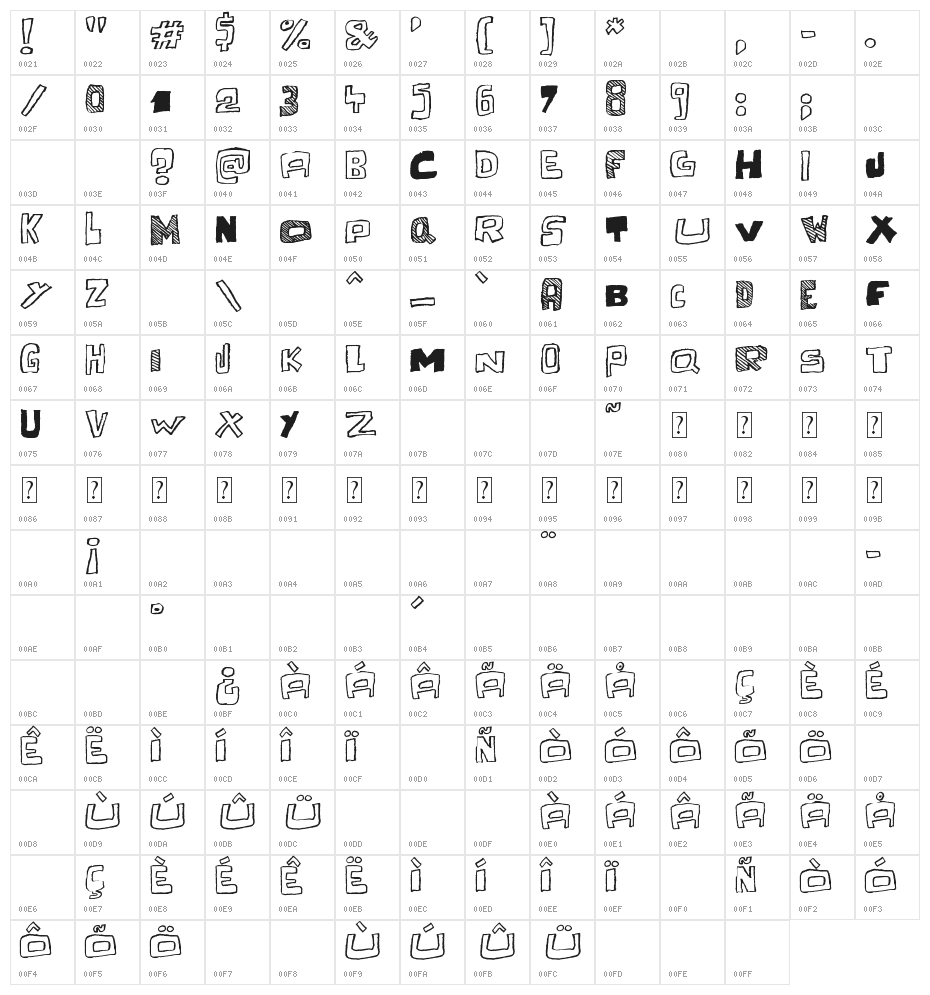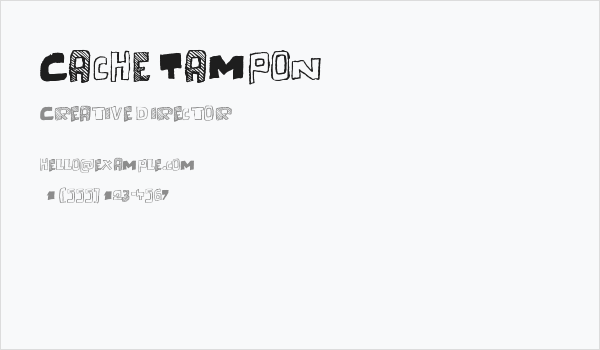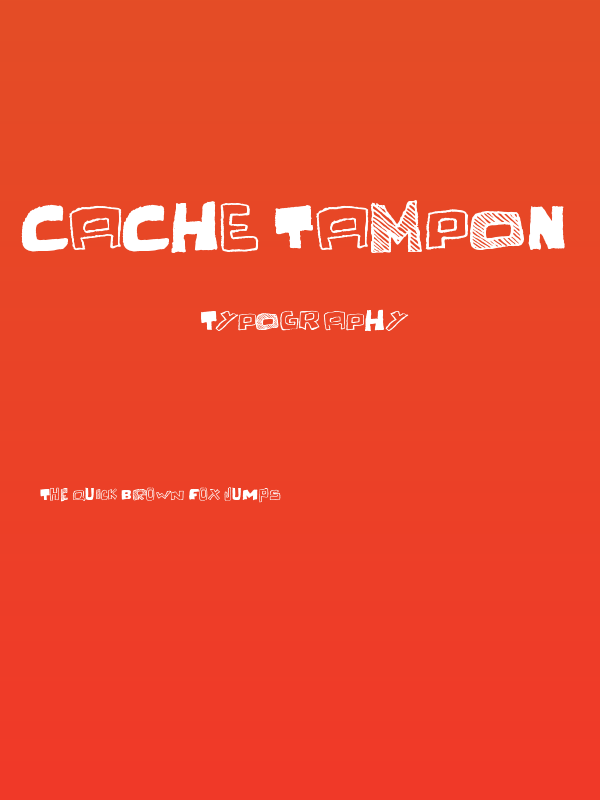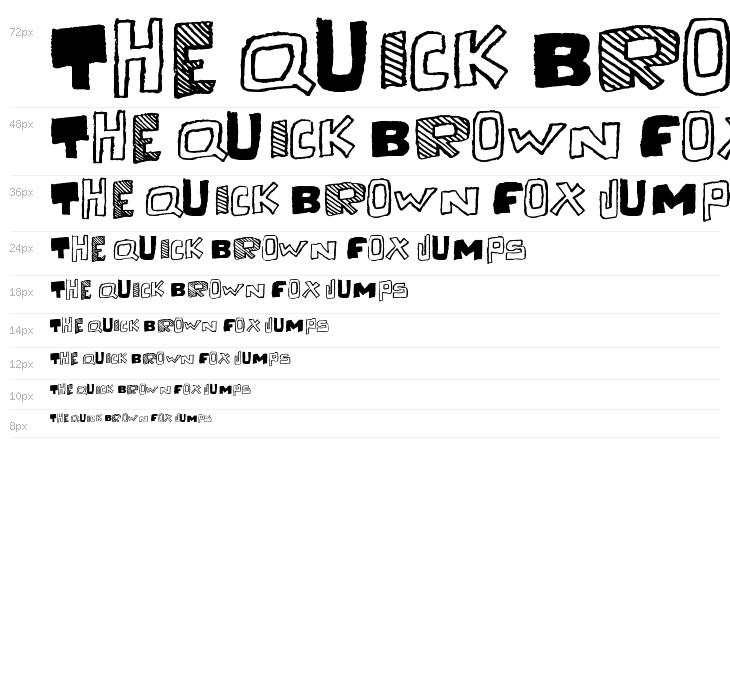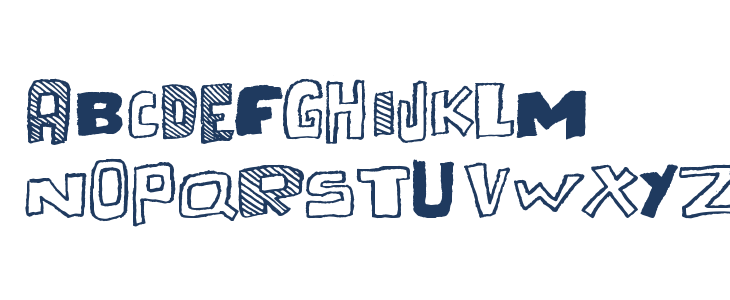
Cache Tampon Font
| Stil general | Playful, Energetic, Informal |
| Caz de utilizare | Headlines, Posters, Creative Designs |
| Proiecte propuse | Ideal for children's books, comic strips, creative posters, and informal designs. |